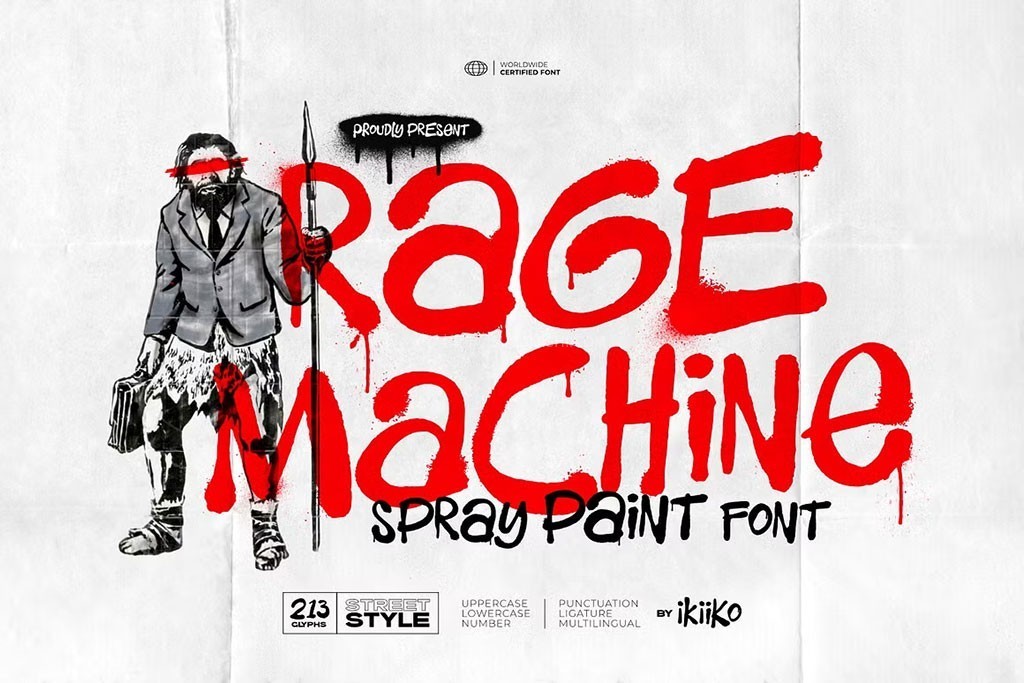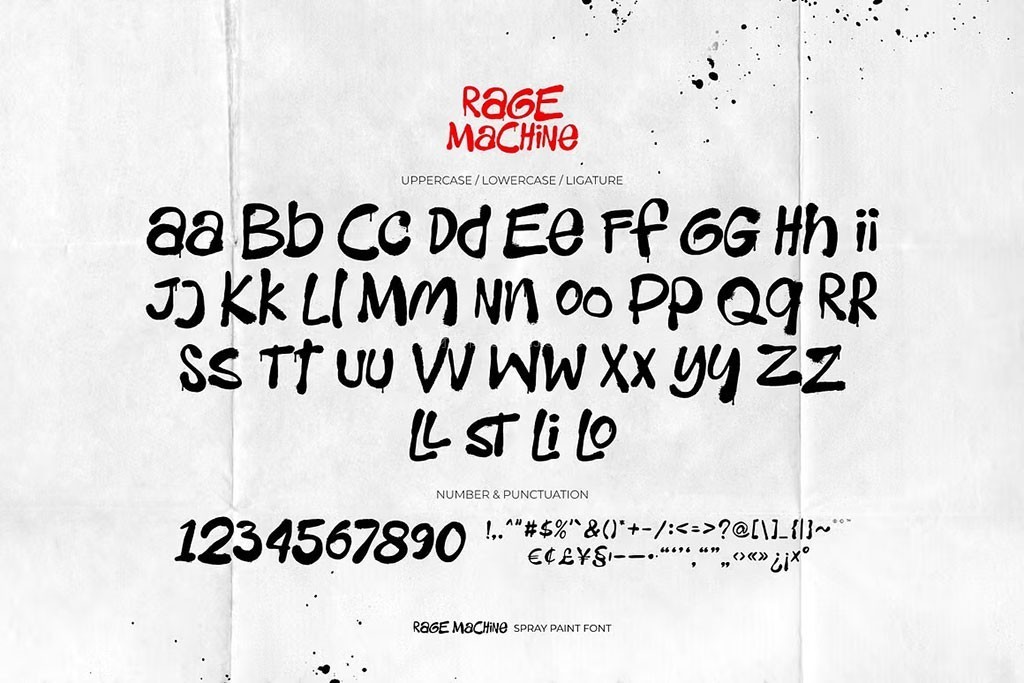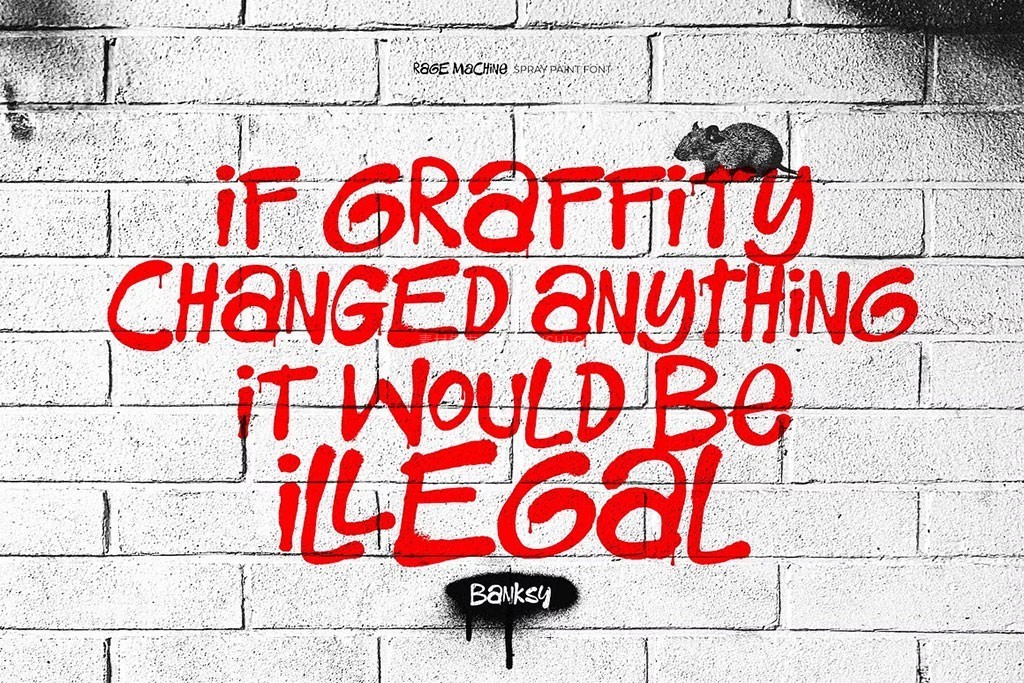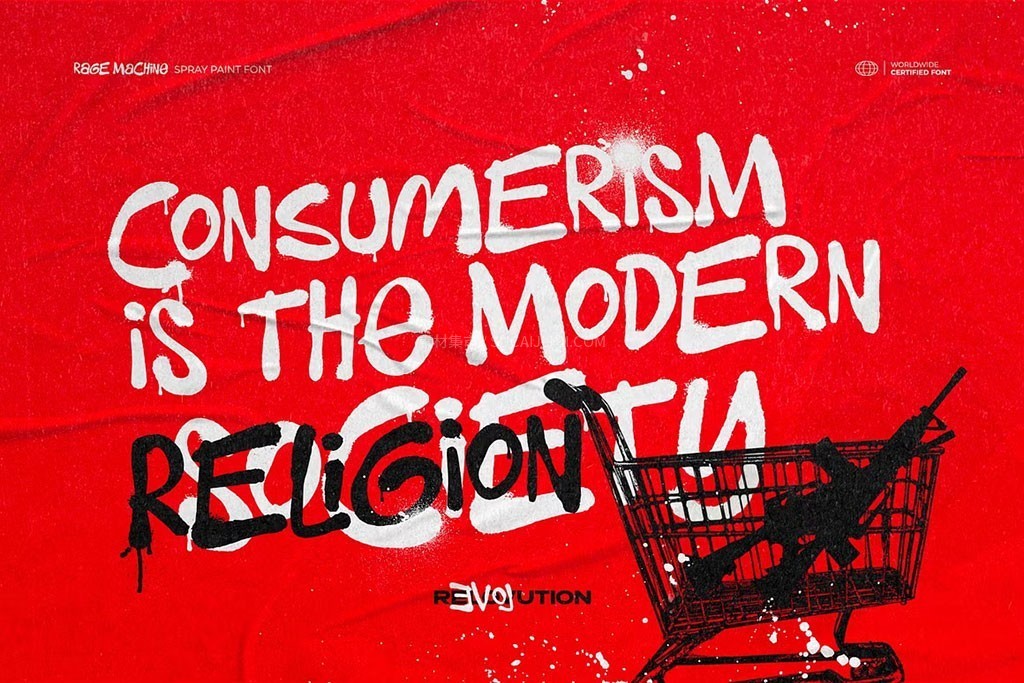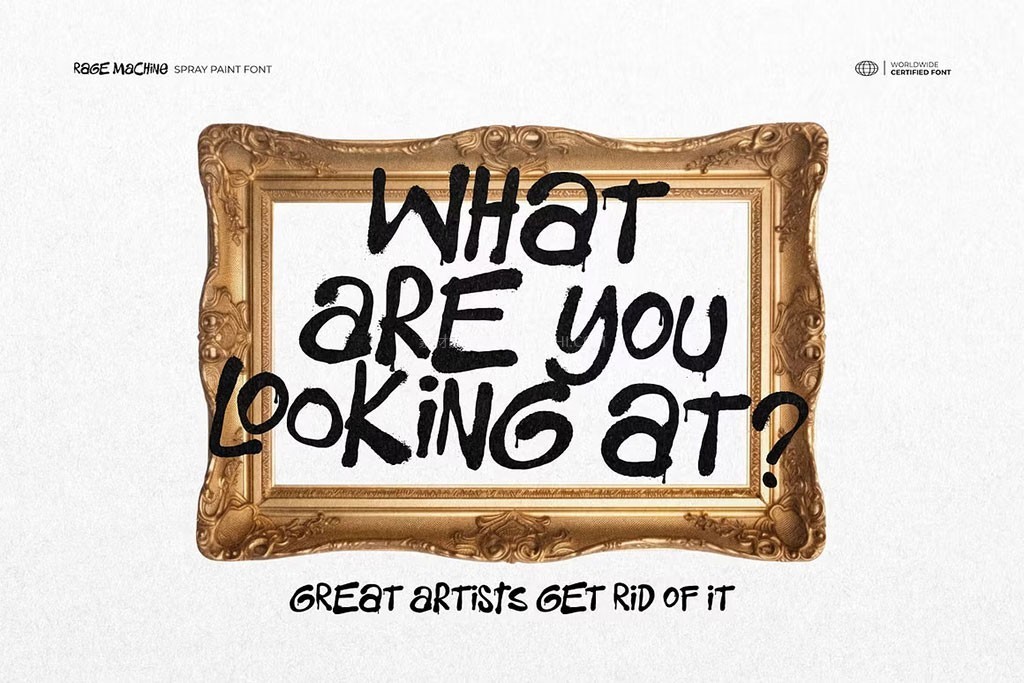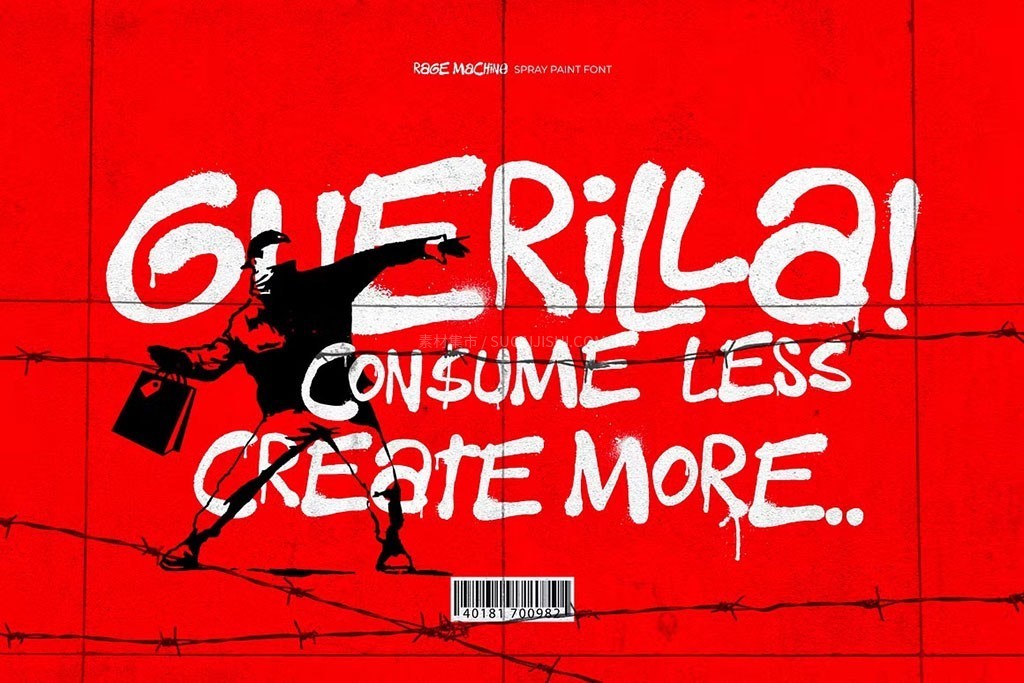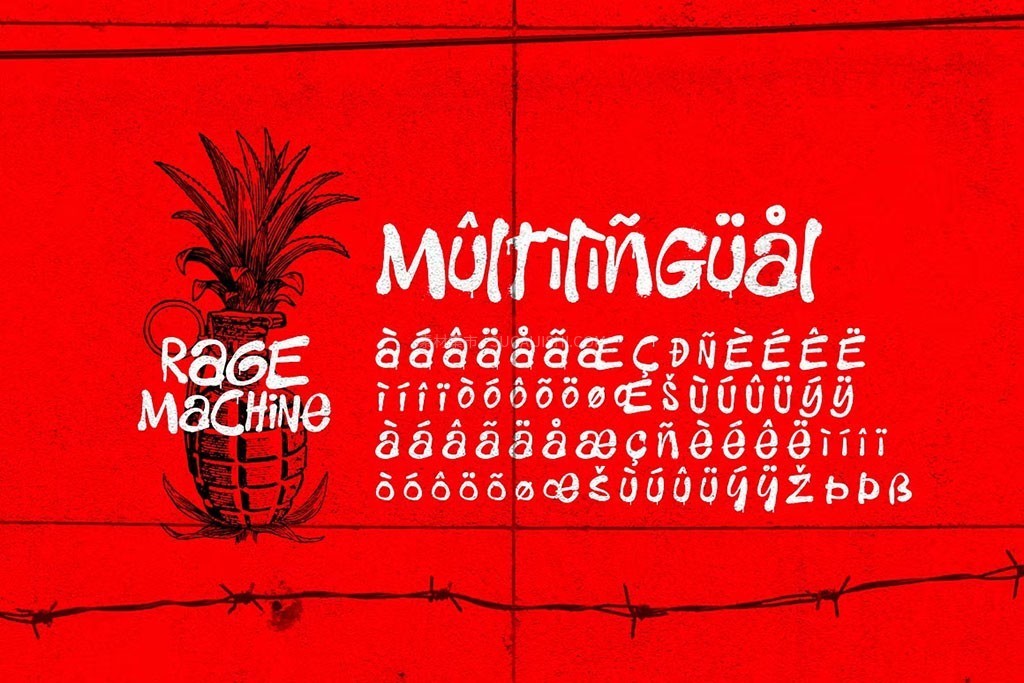
Rage Machine 手绘涂鸦喷绘字体
Rage Machine 采用粗犷的喷绘质感,精准复刻了颜料喷涂在砖墙与城市建筑上的真实纹理。它不仅是一款字体,更是表达自由、反叛与都市个性的有力宣言。无论是打造醒目的海报标题、时尚街头服饰设计,还是为艺术创作添加动感文字叠加层,它都能为你的作品注入浓郁的“街头不羁”氛围,让视觉冲击力直抵人心。